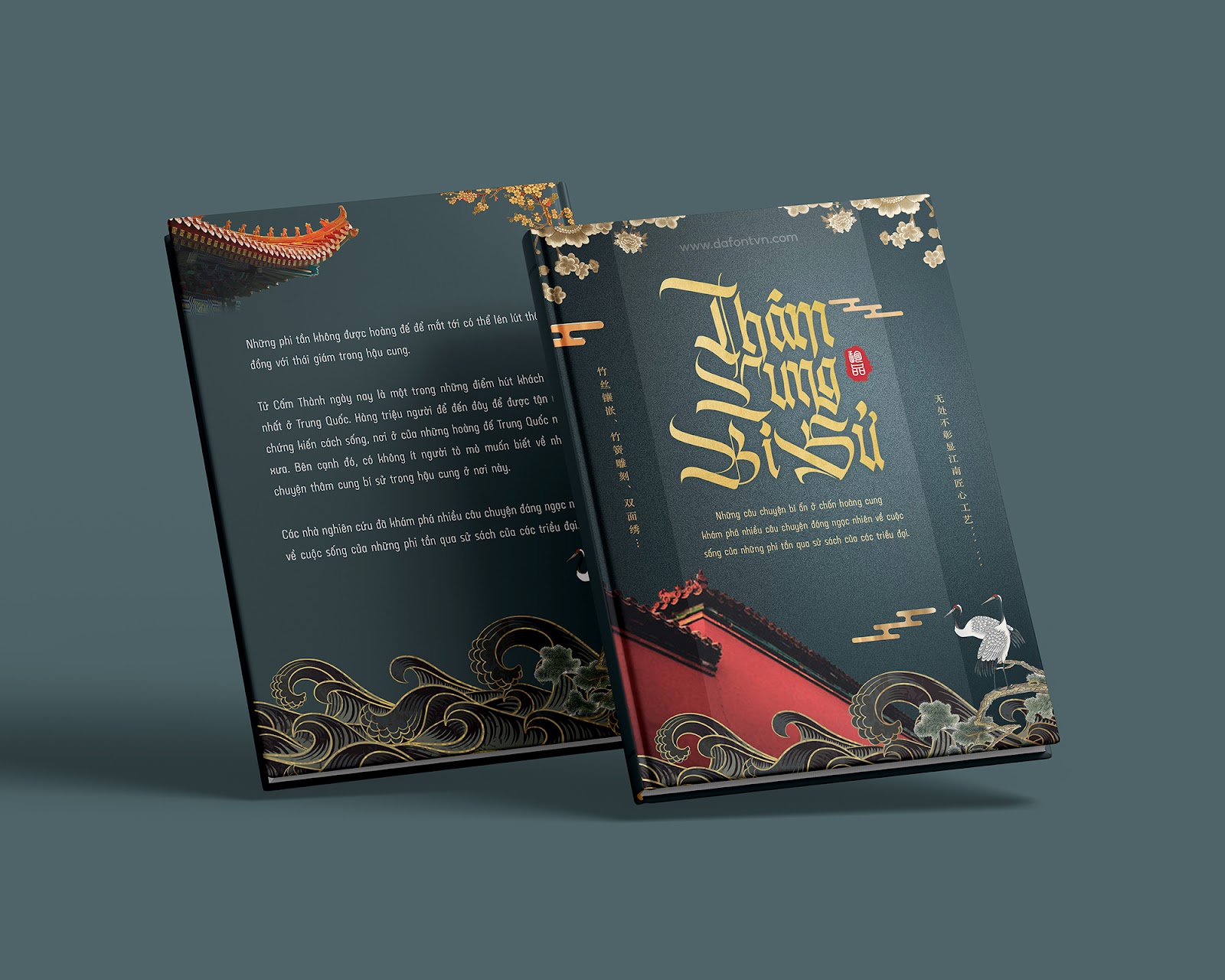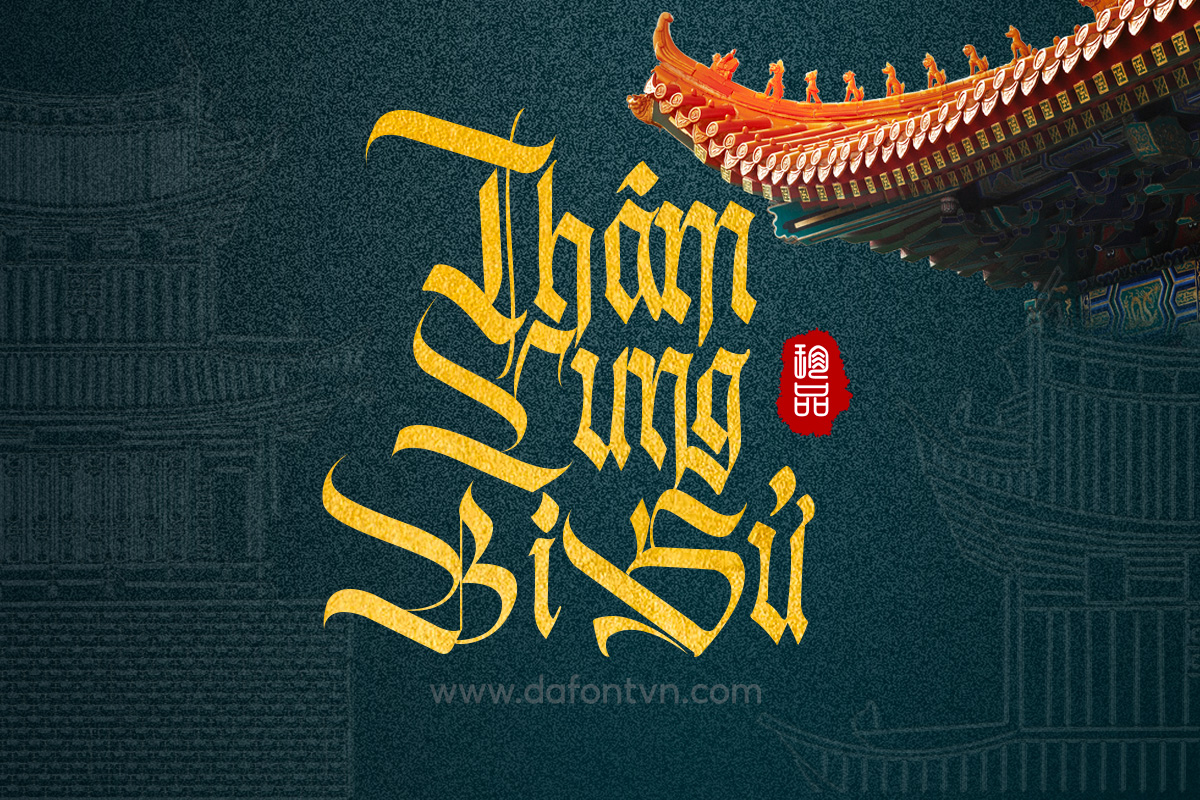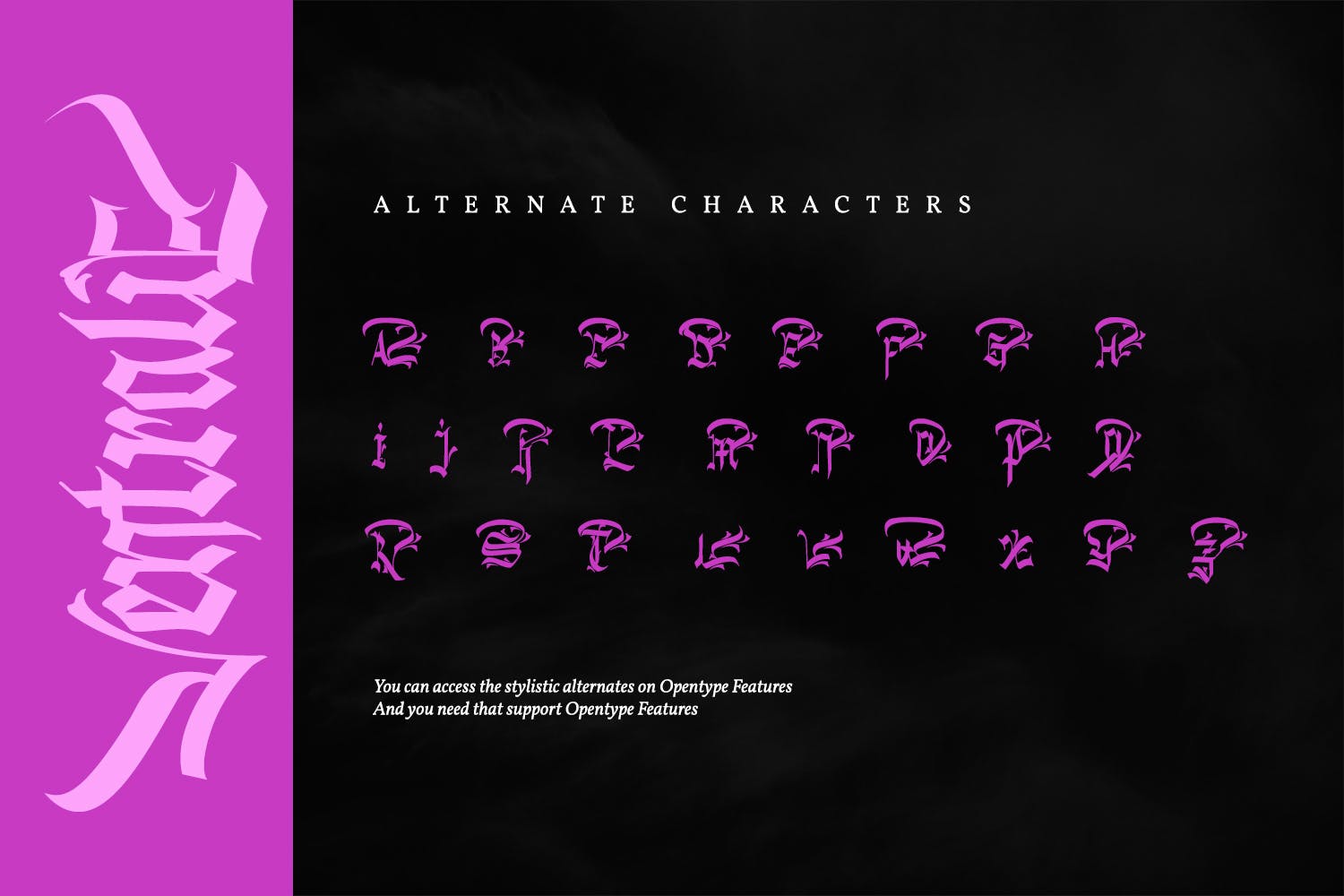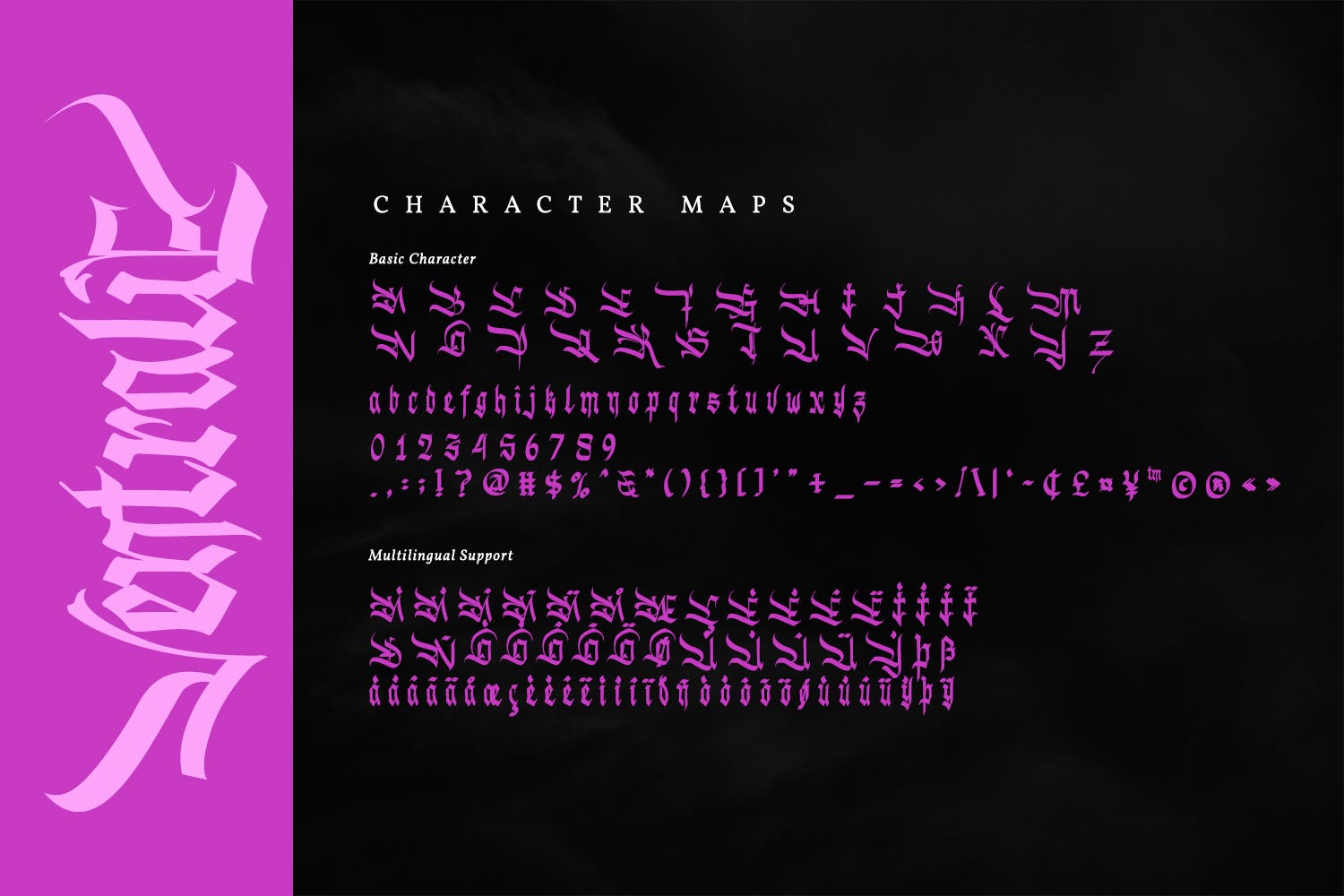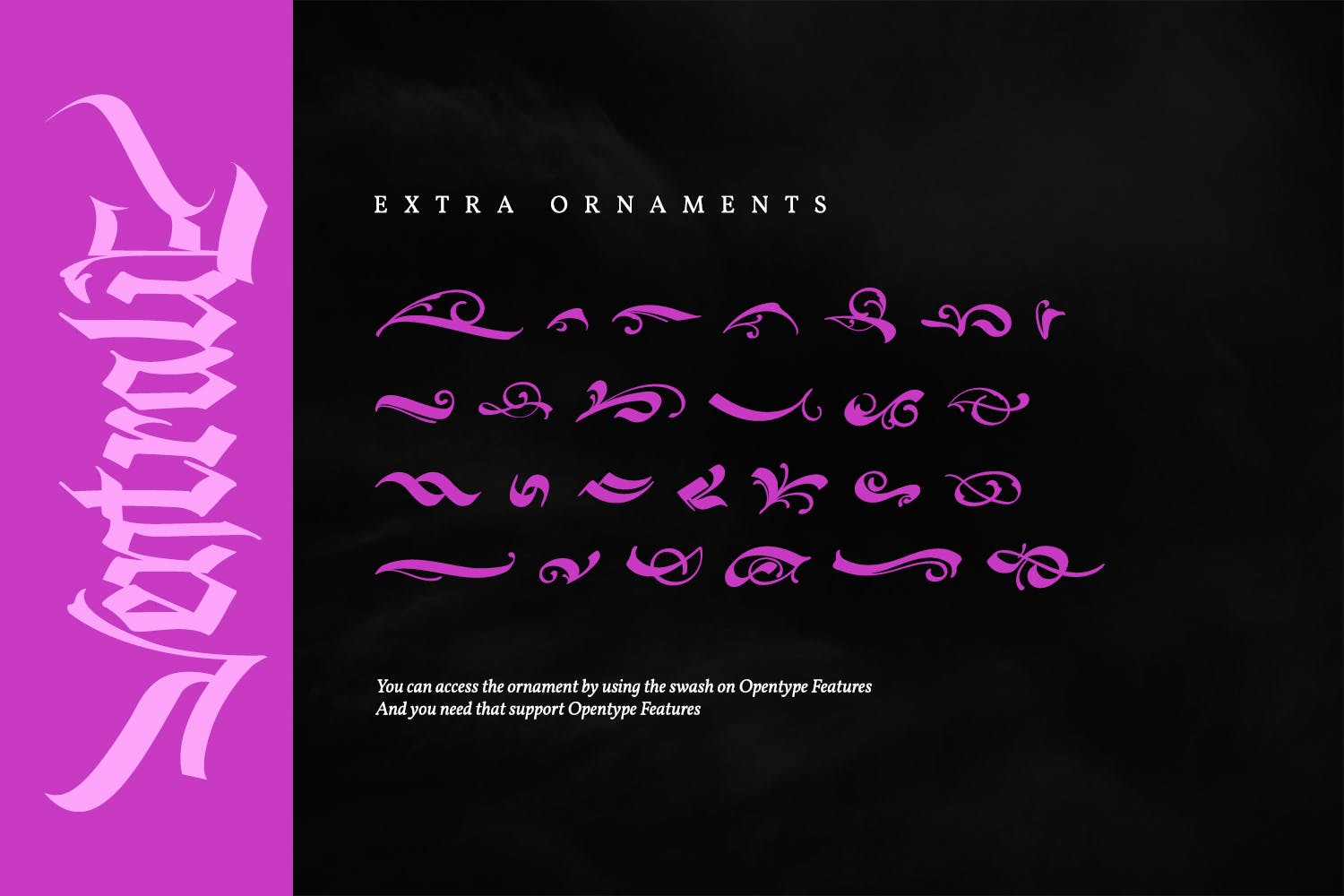
Font Ventralie Việt hóa – Phù hợp thiết kế cổ trang
Font Việt hóa Ventralie – Một font chữ khá phù hợp dành cho các thiết kế cổ trang, dành cho các bạn thiết kế bìa sách, bìa truyện, trang trí hay bất kỳ thiết kế nào khác đòi hỏi một font chữ đẹp và lạ mắt.
Font việt hóa đầy đủ, kerning, feature, ngoài ra font còn bao gồm các ký tự thay thế và mã hóa PUA.
Font cổ trang việt hóa Ventralie
Font Ventralie Việt hóa
Ventralie - Blackletter Font Việt Hóa